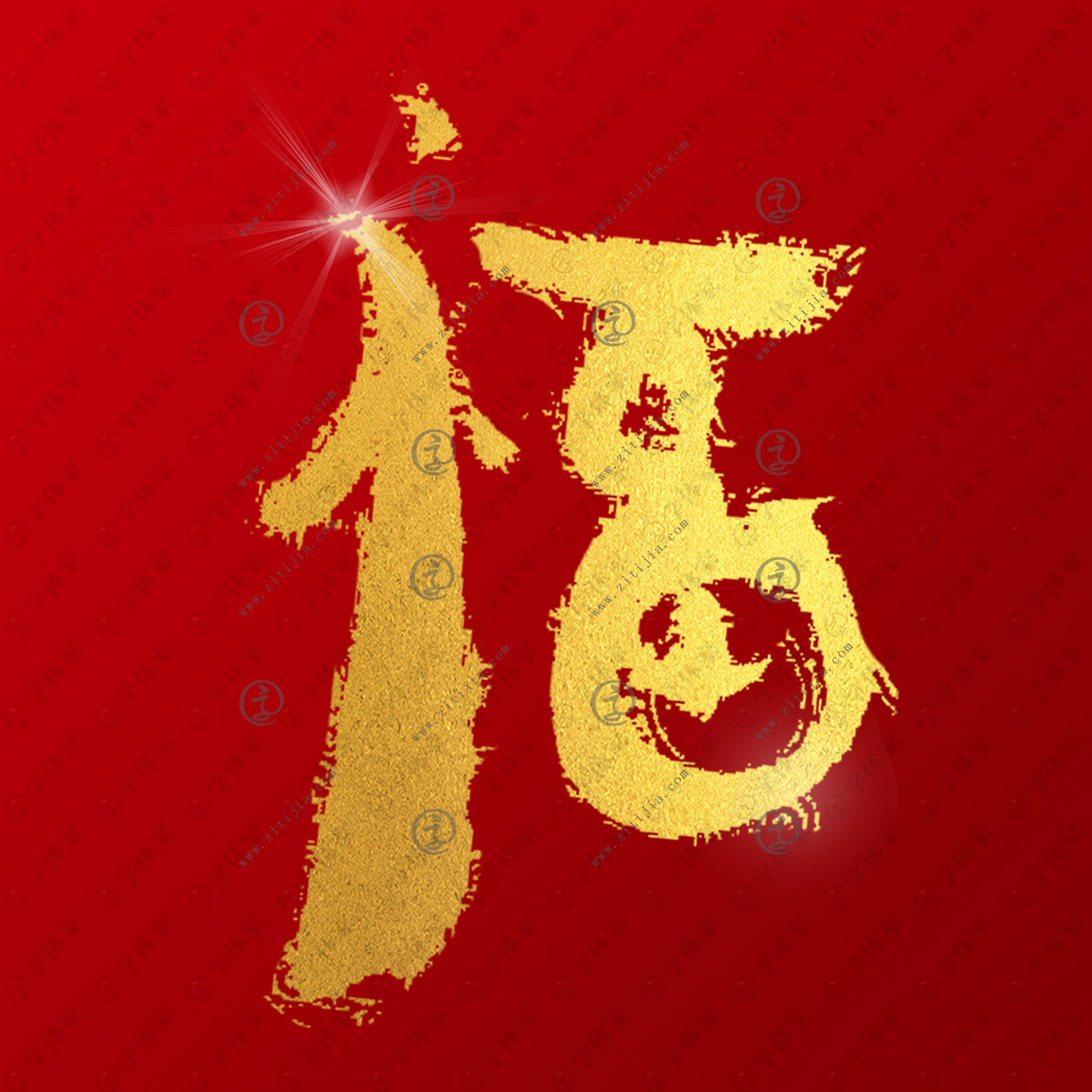
福字书法素材原创字体下载可商用
福,会意兼形声字。从河南殷圩出土的甲骨文来看,“福”是双手虔诚地捧着酒坛(酉)敬神(示)的形象,是用“手”、“酒”、“示”三个部分组合成的会意字,原是以酒敬神,祈求福备(万事顺遂)的意思。从上列甲骨文字形来看,它的左半部的上面是个“酉”字,是个盛酒的容器,实际上就是个“酒”字的初文。左下半部分是两只“手”(又),表示双手捧着一个酒樽;它的右半部分是个“示”字,代表祖先的神主;整个字的意思是会意双手捧着一樽酒在祖先的神主前祭献,求得神主保佑。《说文解字》在解释“福”字的意义时说“祐也”,“祐”就是赐福、保佑的意思。